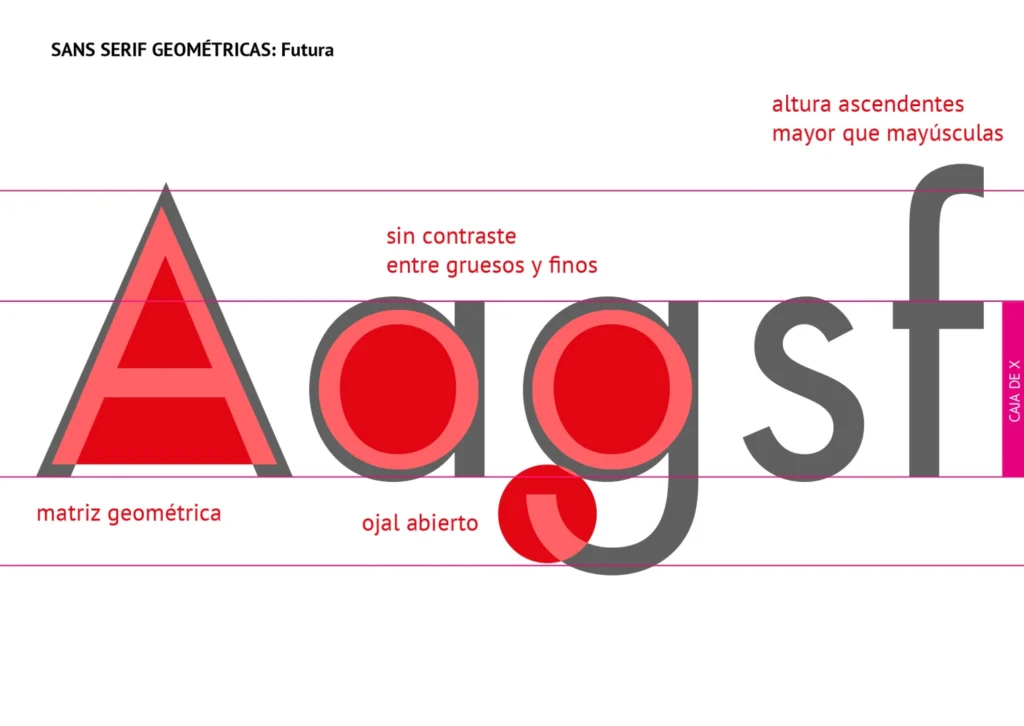
Las geométricas, según la clasificación de la Asociación Tipográfica Internacional (ATypI) son tipografías pertenecientes a una subcategoría de la lineales o sans serif, (siendo las otras subcategorías: Grotesca, Neogrotesca y Humanista).
Están basadas en formas geométricas básicas como el círculo, el cuadrado o el triángulo. Frecuentemente presentan una perfecta redondez de la «O» y una estructura sencilla en la «a».
No son apropiadas para bloques de texto largos.
Ejemplos: Futura, Avant Garde, Avenir, Century Gothic.